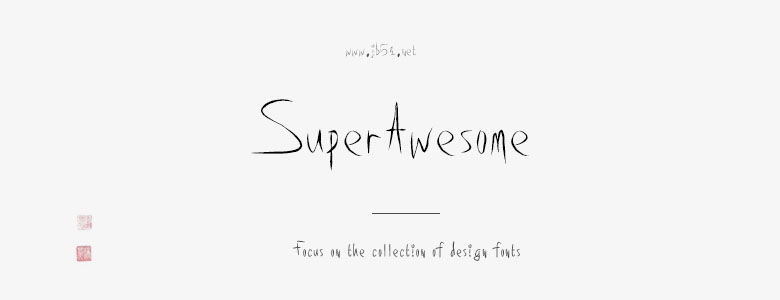
Super Awesome英文手寫(xiě)字體,字體筆觸纖細(xì),書(shū)寫(xiě)流暢,具有很好的視覺(jué)感,適合應(yīng)用于藝術(shù)設(shè)計(jì)、平面宣傳設(shè)計(jì)、網(wǎng)頁(yè)設(shè)計(jì),書(shū)法字帖等領(lǐng)域。有需要的朋友快來(lái)本站下載使用吧。